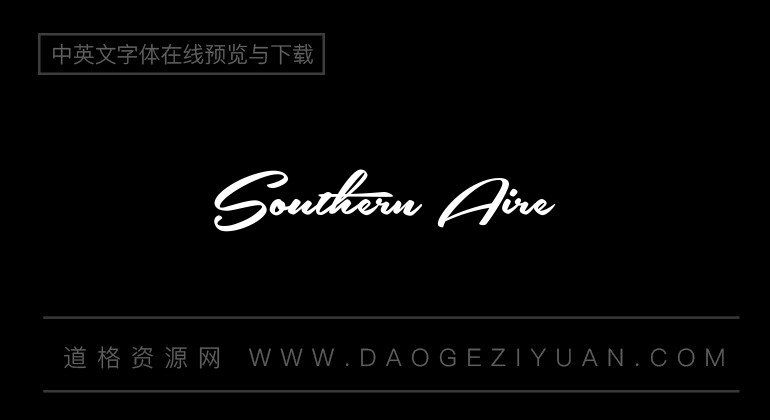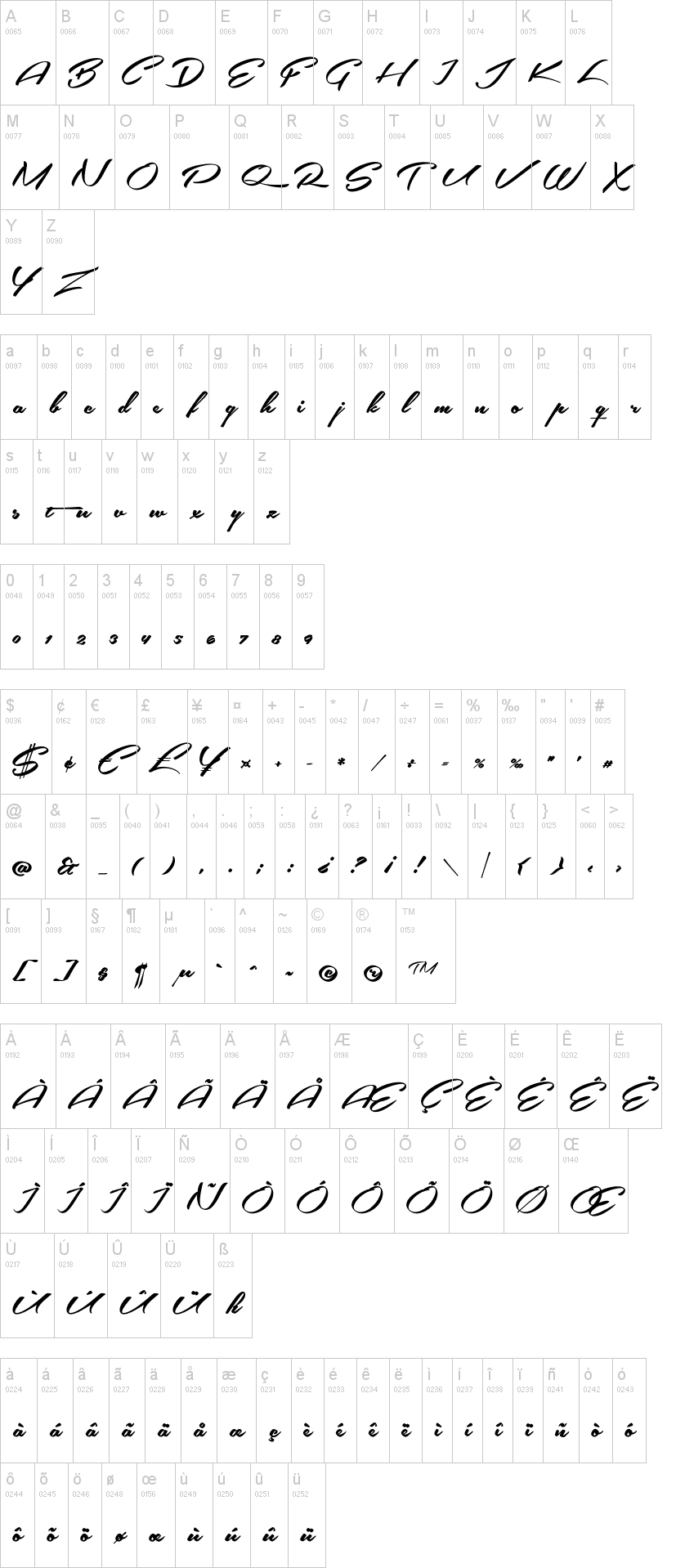
Southern Aire
Southern Aire是一款由著名设计师Jeff Levine设计的字体,它具有传统的南方风格,特色是细节的处理,尤其是英文字母的曲线和边缘的处理,使得字体具有轻松感,把南方风格表达得淋漓尽致。Southern Aire字体可以用于多种不同的应用,如广告、标识、社交媒体、内容标题等,具有良好的可读性和可视性。
Southern Aire是一款非常不错的手写艺术字体,具有很好的视觉感,适合于文化类的宣传设计、商业类品牌的广告和产品包装设计以及个性化文字排版等较多场景。